Perseverancia, paciencia infinita, respeto inquebrantable y amor incondicional por un oficio tan bello como sacrificado que, a pesar de que el advenimiento digital certificó su defunción, goza de buena salud. Y paradójicamente han sido precisamente las redes sociales el medio para mostrar al mundo que todavía hay quien se dedica profesionalmente al oficio del rotulismo tradicional a pincel.
Formada en el diseño gráfico, Elisa muy pronto descubrió que al margen de la pantalla del ordenador seguían existiendo amplias parcelas de creatividad donde poder dar rienda suelta a su expresividad más personal. Tras un máster de caligrafía, inició una fructífera carrera de rotulista que la ha llevado de su natal Granada, pasando por Barcelona, hasta Berlín, donde actualmente reside. Hoy en día es una referencia indispensable del rotulismo a pincel en España.
Hemos hablado con Madame Letters de muchas cosas, como descubrir el propio camino, también del pánico al papel en blanco y a saltar al vacío. Seguir una vocación es como subir la montaña por el lado más escarpado, pero hay quienes como ella, a pesar de las dificultades e incomprensiones, disfruta de cada paso porque está convencida de la bondad intrínseca de los materiales que conforman su día a día.
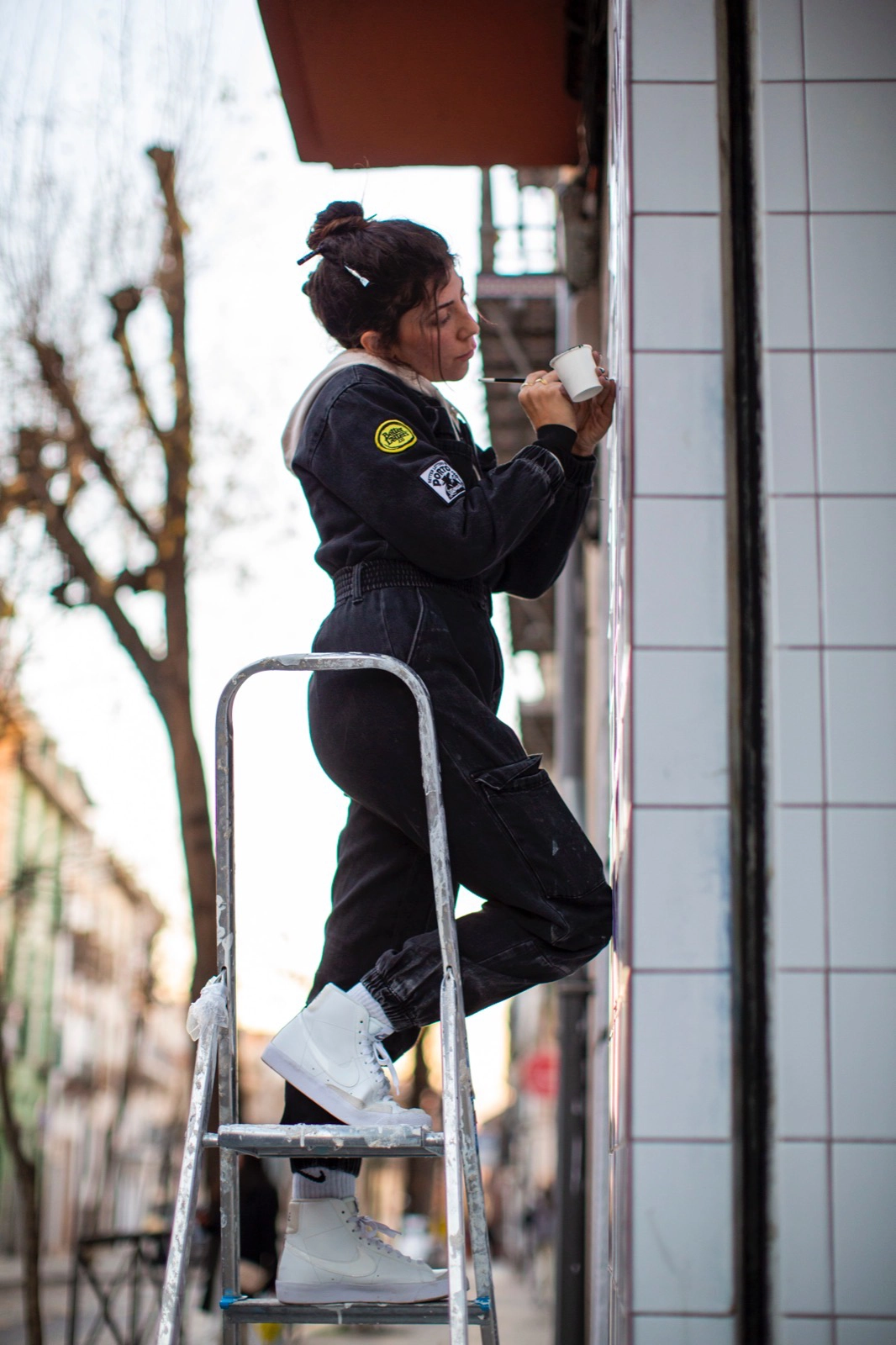
AKA DELE. Proceso
¿Cómo descubriste tu pasión por el rotulismo y el diseño de letras?
En realidad fue algo circunstancial. Como la mayoría de rotulistas de mi generación ( y de las posteriores) tengo formación en diseño gráfico, aunque la mía fue corta y me dejó con inseguridades y poca práctica. Por eso lo completé con un máster donde descubrí el mágico mundo de la caligrafía. Dejar el ordenador a un lado despertó una parte en mí que, aunque ya pintaba al óleo desde pequeña, había menospreciado hasta el momento. Nunca tuve el interés y la paciencia para diseñar tipografía digital y por eso admiro muchísimo a las personas que lo hacen.
La rotulación llegó a mi vida más tarde cuando, paseando por la convención de tatuajes de Barcelona, vi un pequeño stand de una pareja haciendo una demostración en vivo y dando a conocer el oficio (más común entre tatuadores). Me sentí conmovida, como si acabara de descubrir lo que llevaba tanto tiempo buscando, sin saberlo.
Siempre me sentí «mediocre» cuando estudiaba. Mis trabajos eran de lo más normal. Ahora veo que simplemente estaba aprendiendo y no era un lugar donde competir ni compararse. Esto, en rotulación, es uno de los pilares fundamentales. En general, somos una comunidad pequeña y humilde. Nos encanta compartir y ayudar.
Barrio. Specialty coffee (Granada)
¿Qué te llevó a elegir el rotulismo como carrera profesional?
Cuando asistí a mi primer taller de iniciación sentí como si mi eterna búsqueda hubiera terminado. Nada más lejos de la realidad, un mundo nuevo se abría ante mí y hasta día de hoy sigo explorando y aprendiendo.
También me di cuenta de que no iba a ser fácil: dominar el pincel requiere mucha práctica; el material es caro y para colmo muy pocos saben que este oficio aún existe. En general, parecía un oficio muy sacrificado en muchos sentidos, pero mi experiencia en caligrafía, tipografía y diseño me daba tal seguridad que pensé que sólo era cuestión de práctica. Esa noche llamé a mi madre para decirle que ya lo había decidido: —Mamá, voy a ser rotulista.
Lo que me cautiva de la rotulación (de la artesanía en general) es que cada trabajo es único. No hay espacio para competir entre nosotros. Excepto quien busque la fama o el reconocimiento personal como artista, creo que todos perseguimos un mundo mejor donde las ciudades son más bonitas y los negocios más humanos.
Amarela Cafe. Proceso
¿Quiénes han sido tus mayores influencias o referentes en el mundo del lettering y el diseño?
Sin duda Keith Adams, quien me enseñó el amor por la caligrafía y por la enseñanza, que ni es fácil ni está hecha para todo el mundo. También a mi querido amigo Anibal García, a quien admiro por haber encontrado el balance entre ser un prolífico diseñador y llevar una vida rural y disfrutar de las cosas importantes de la vida.
¿Recuerdas algún proyecto o experiencia inicial que te marcara especialmente?
Recuerdo la primera vez que alquilé un taller en Barcelona, donde vivía en ese momento. Era verano, tenía 25 años y había dejado mi trabajo de oficina para empezar de cero. Apenas tenía tres latas de pintura y dos pinceles. No tenía experiencia ni encargos. Una tarde de agosto de muchísima calor y con un folio en blanco delante de mí, experimenté mi primer ataque de pánico, que me marcó para siempre. Varios ataques y angustias más tarde, me mudé a Granada, mi ciudad natal, donde me recuperé y lo intenté de nuevo, a mi ritmo y de una manera más amable. Esto me ayudó a entender que el éxito exige tiempo y perseverancia; a no vivir por encima de tus posibilidades y a disfrutar más los comienzos.
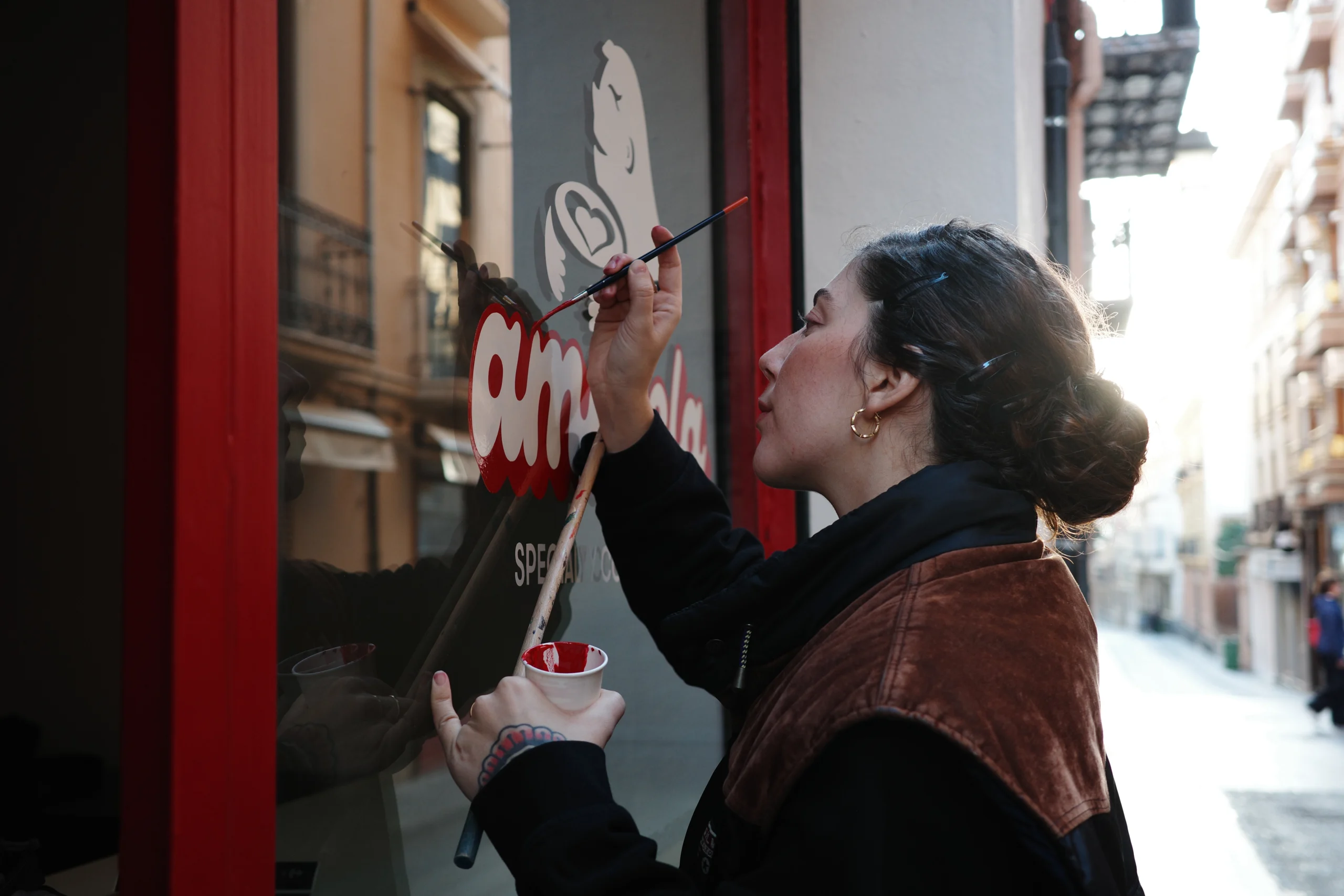
Amarela Cafe. Proceso
¿Cuál es tu proceso creativo al enfrentarte a un nuevo proyecto? ¿De dónde sacas inspiración?
Cuando ya conozco el nombre y el negocio que voy a diseñar, experimento una especie de sinestesia lingüística: puedo ver colores, formas o estilos de letra concretos, e intento ser fiel a este primer estímulo. Esto no pasa por arte de magia, sino por años de experiencia, ensayo y error. Nunca lo he hablado con nadie pero imagino que nos pasa a la mayoría. Antes me dedicaba a hojear libros y bocetar hasta dar con algo decente. Me inspira mucho la rotulación francesa; su paleta de colores y tipografías tan exquisitas y delicadas, en oposición a lo que a uno puede venirle a la mente cuando piensa en la rotulación tradicional norteamericana, de la que bebemos la mayoría de rotulistas al empezar.
Burds of the brush da especial bienvenida a mujeres, personas queer, transgénero y no binaries donde no hay espacio para dinámicas sexistas, machistas, racistas, homofóbicas ni transfobas. De hecho, me enorgullece formar parte de la organización del próximo encuentro inclusivo en Berlín el próximo mes de septiembre.
Benditas mujeres tattoo. Boceto